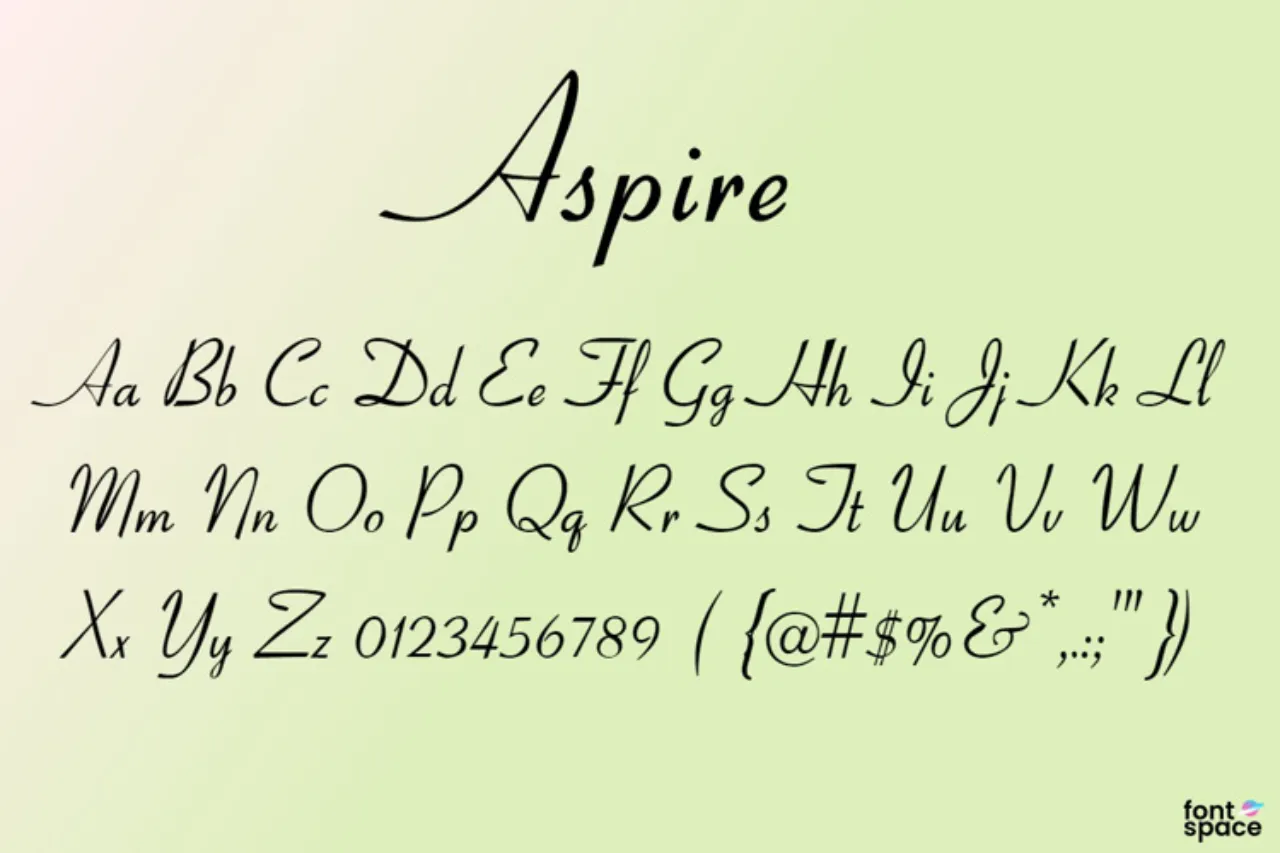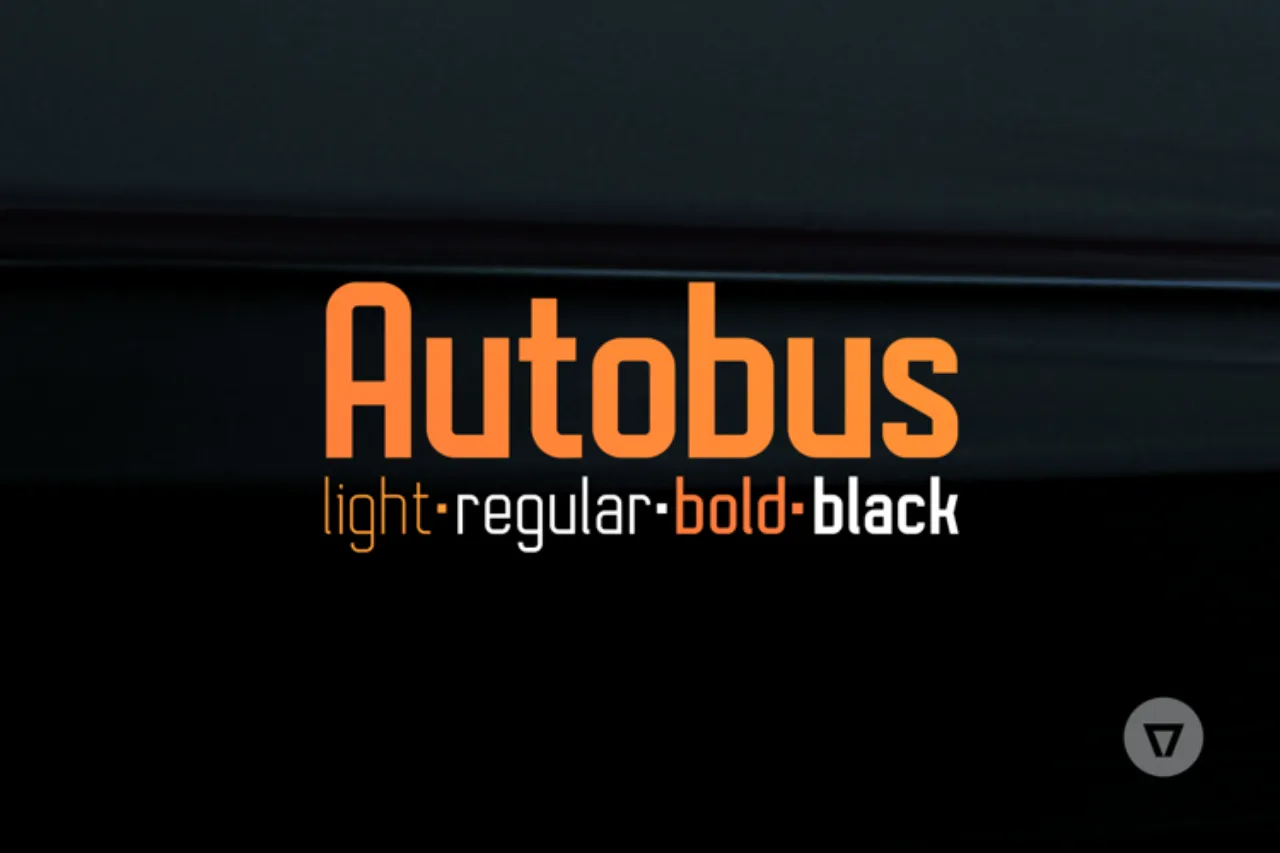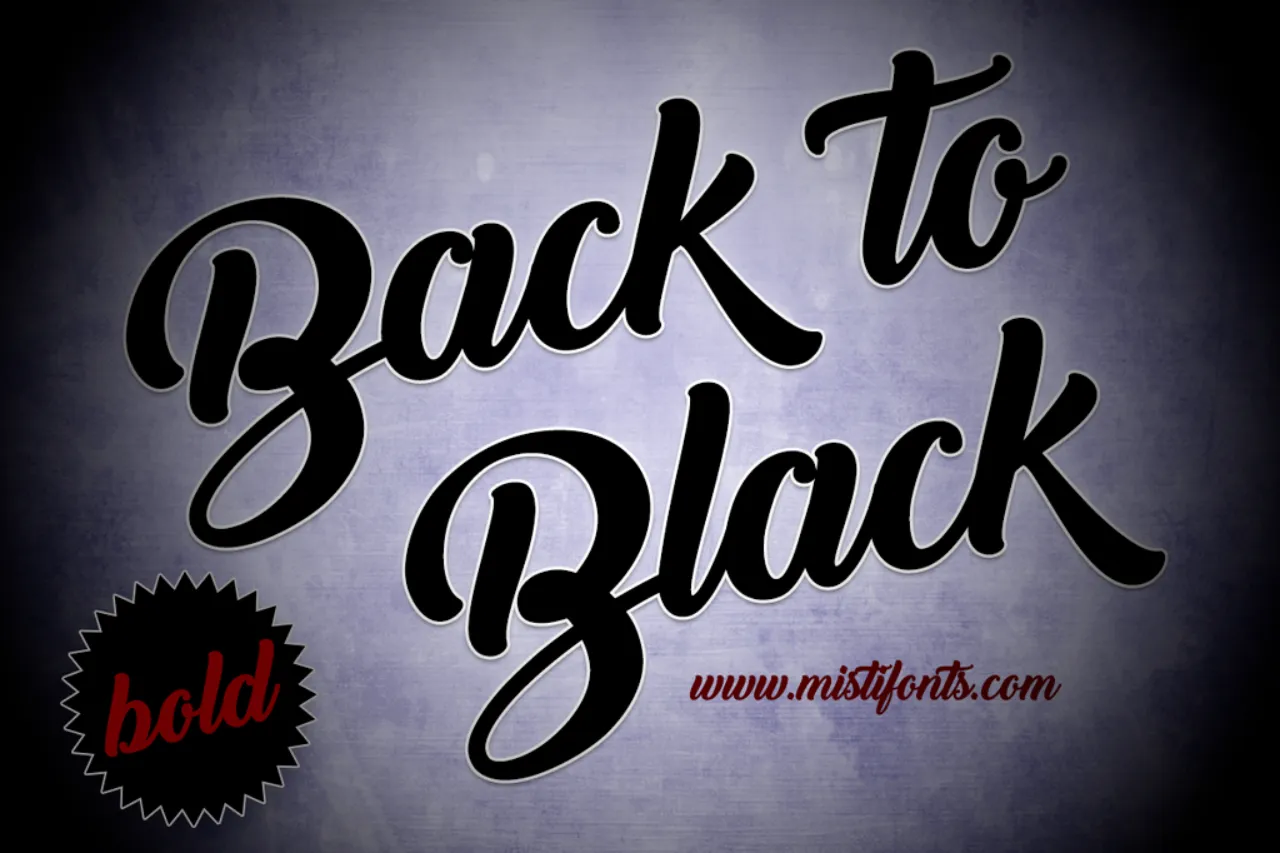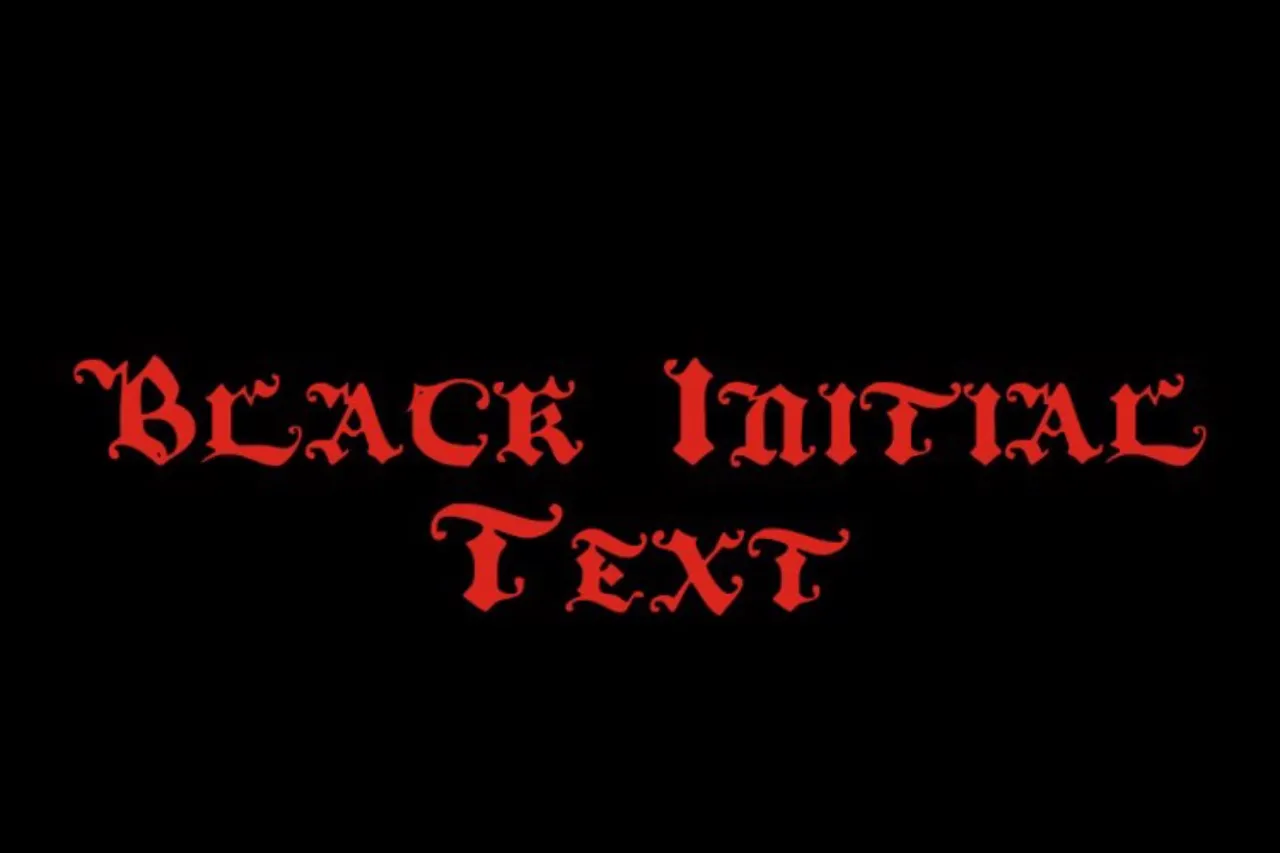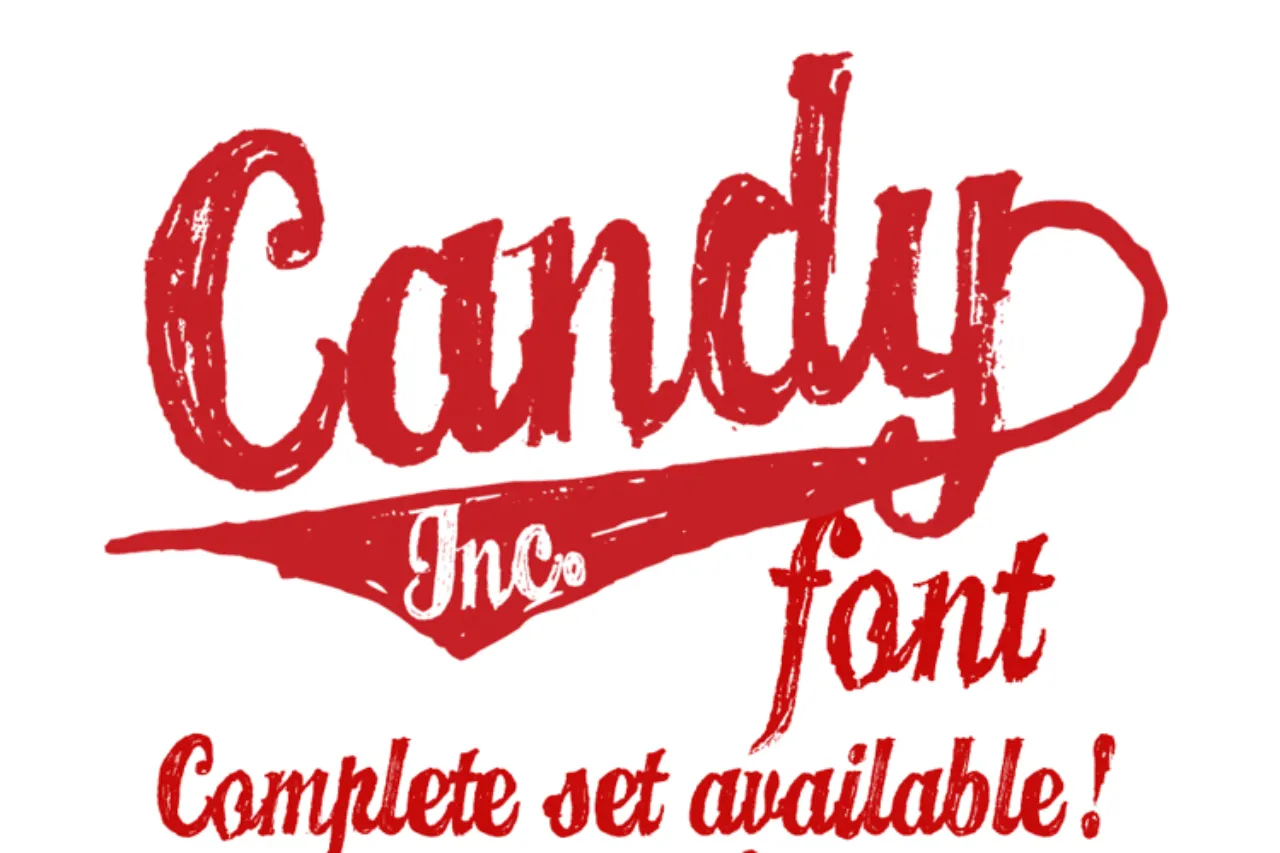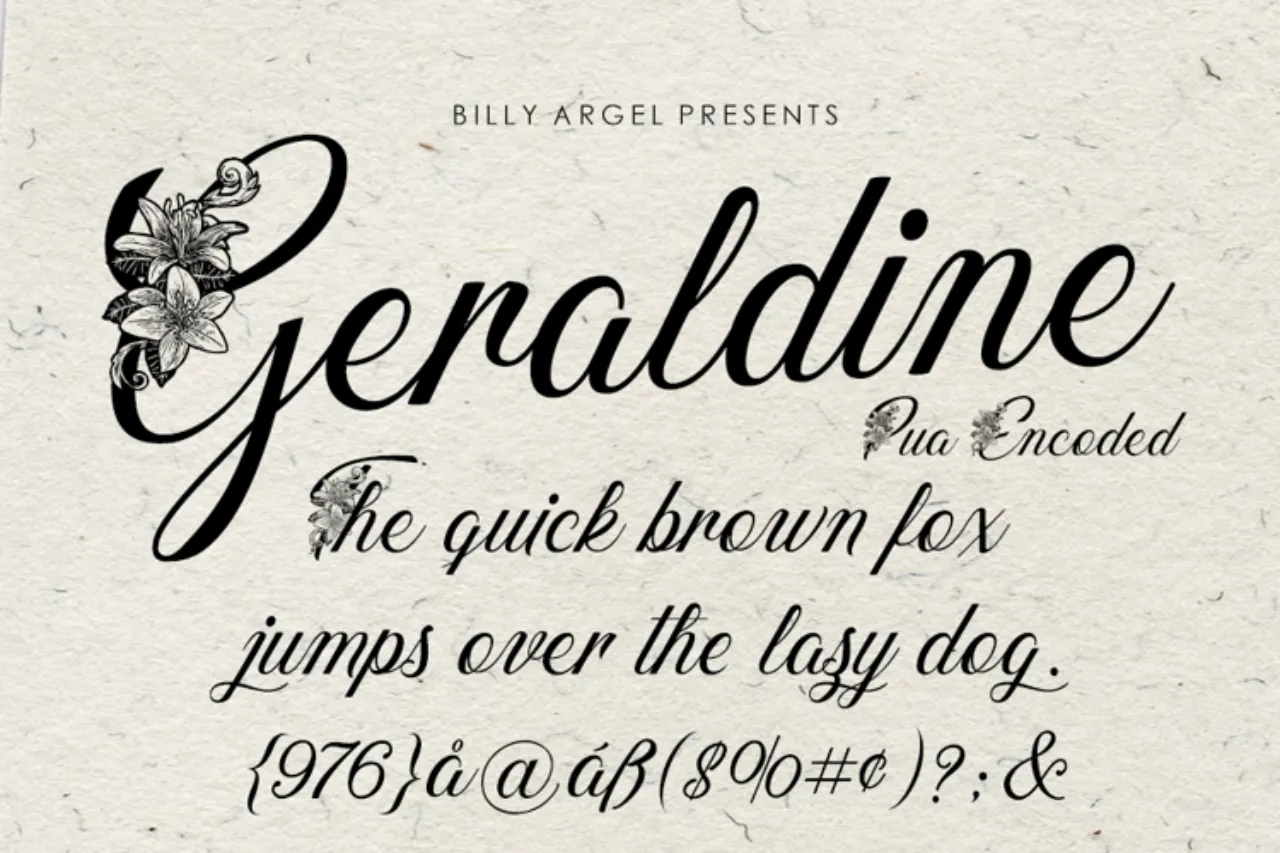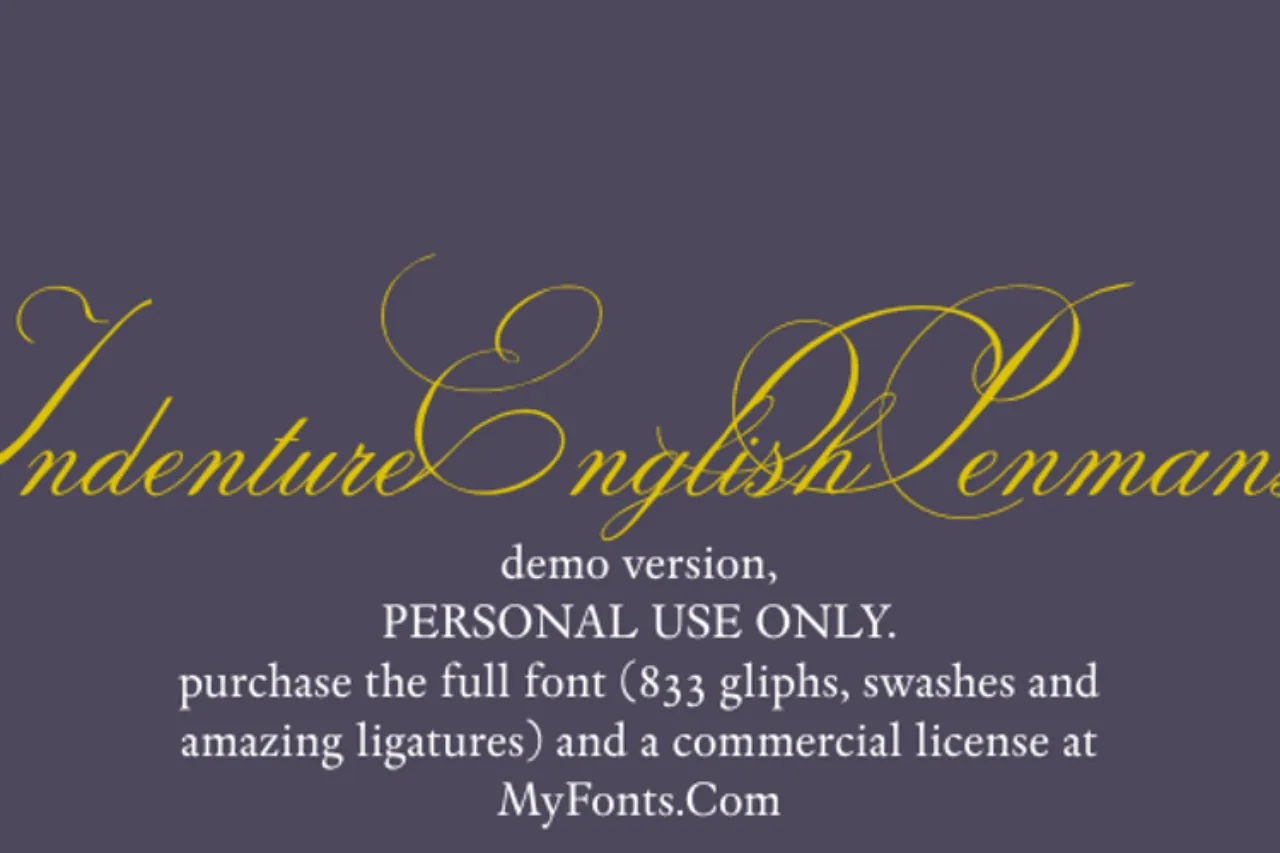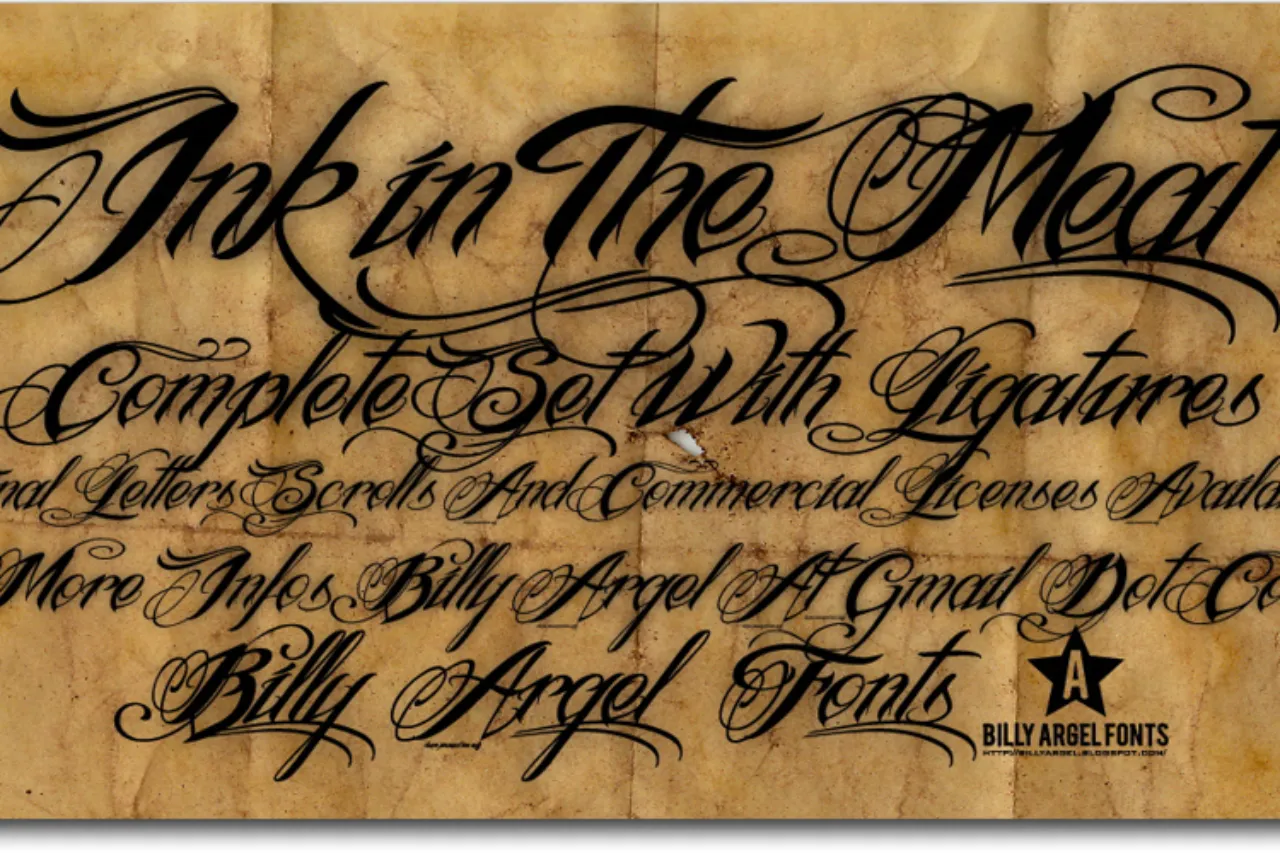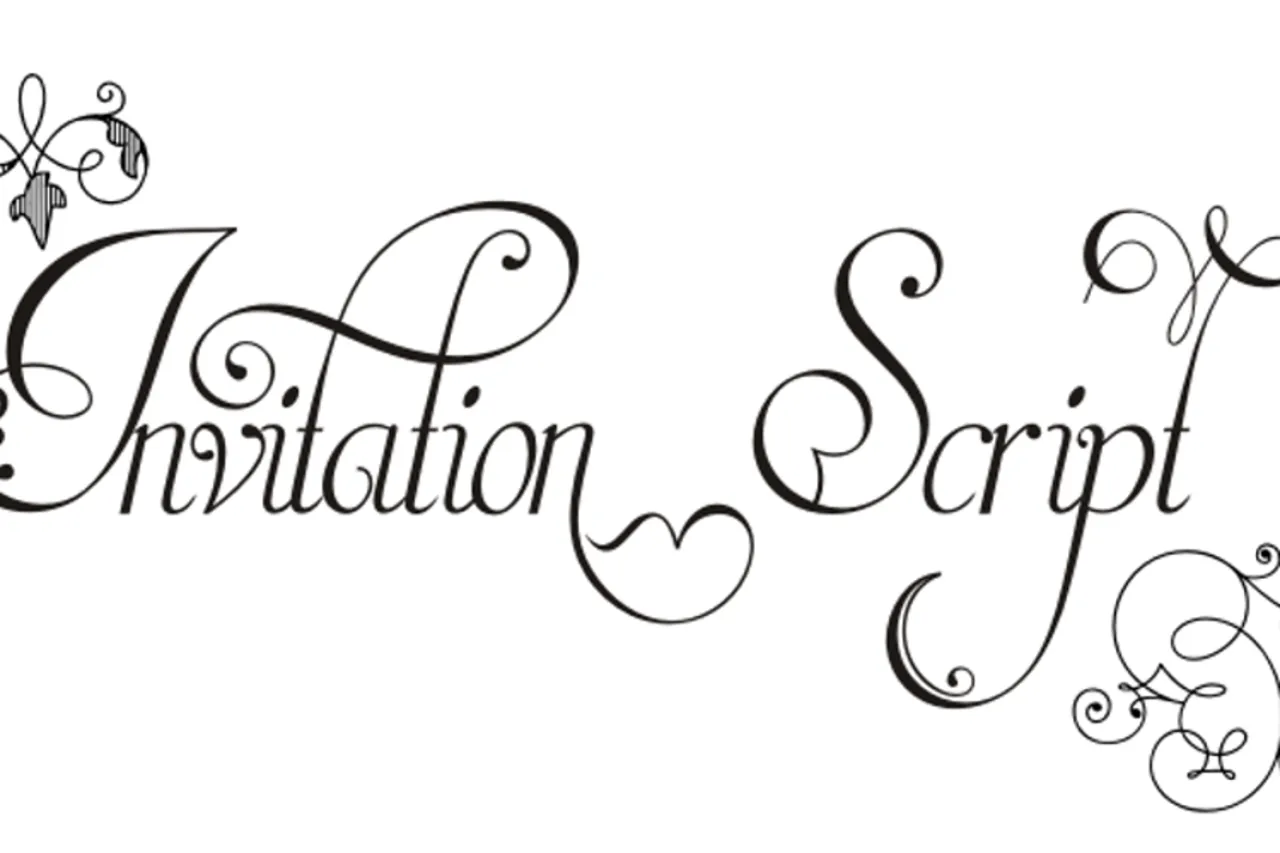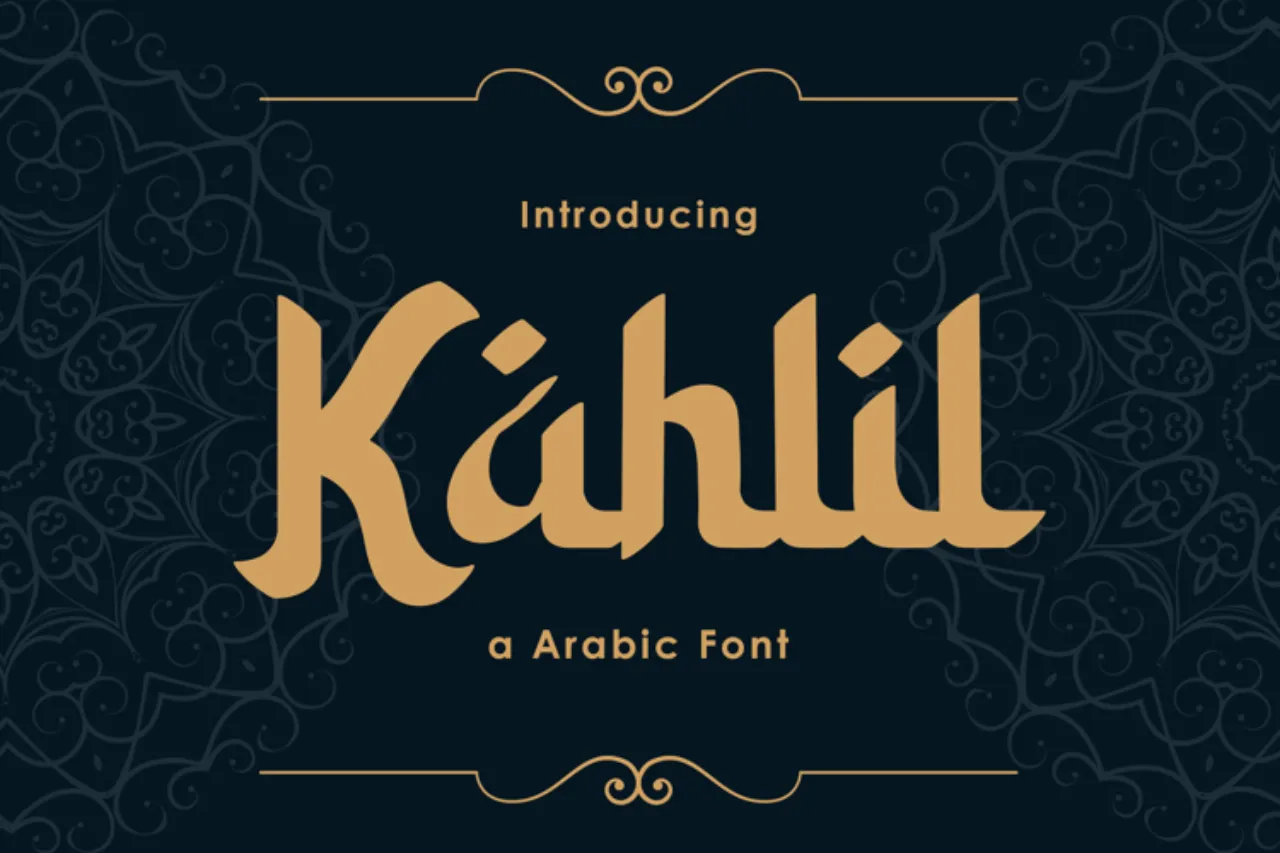
Font Sertifikat
25 Rekomendasi Font Sertifikat dan Link Downloadnya
Sertifikat dan piagam adalah salah satu dokumen yang cukup penting. Karena sertifikat dan piagam ini sering dipakai sebagai hadiah dari pencapaian seseorang setelah mengerjakan sesuatu.
Oleh sebab itu, sertifikat harus didesain sebaik mungkin untuk meningkatkan kesan menarik. Salah satu yang harus diperhatikan desain sertifikat ialah pemilihan font-nya.
Nah lewat artikel ini, kami akan memberikan daftar font sertifikat dan piagam yang bisa kamu pilih. Kalau penasaran, langsung perhatikan pembahasannya di sini.
Daftar Font Sertifikat dan Piagam Unik dan Resmi
Secara garis besar, font sertifikat dan piagam sering memakai jenis handwriting. Namun terkadang sering juga memakai jenis font lain, tergantung event yang dicapai.
Untuk lebih jelasnya, langsung saja pilih salah satu dari rekomendasi daftar font sertifikat dan piagam seperti berikut:
1. Candy Inc Font
Font Sertifikat Candy Inc
Pertama kamu bisa pakai Candy Inc Font. Font buatan Billy Argel ini memiliki desain yang menarik dan gratis untuk dipakai. Baik untuk kebutuhan desain personal ataupun komersil.
Secara spesifik, desain Candy Inc Font ini mengusung kaligrafi. Namun di dekorasi sedemikian rupa sehingga memiliki kesan sedikit retro.
2. Adine Kirnberg Font Family
Font Sertifikat Adine Kirnberg Font Family
Ada juga Adine Kirnberg Font Family. Dari desain, font ini lebih terlihat modern dari yang sebelumnya.
Namun desain yang ada di font ini lebih simpel, tapi terlihat elegan. Sehingga cocok dipilih untuk membuat sertifikat acara formal.
3. Aspire Font
Font Sertifikat Aspire
Kalau kamu ingin desain font yang lebih sederhana lagi, kamu bisa pilih Aspire Font. Font ini juga sama terlihat elegan, namun dengan dekorasi yang berbeda.
Selain itu, font ini juga sangat cocok untuk dipakai dalam membuat sertifikat formal. Misalnya sertifikat workshop, kursus dan sebagainya.
4. Alex Brush
Font Sertifikat Alex Brush
Kemudian kamu juga bisa pakai Alex Brush. Font ini mengusung desain kaligrafi namun terlihat feminim.
Sehingga sangat cocok dipilih untuk pembuatan sertifikat, piagam, kartu undangan dan lainnya.
5. Ink In The Meat Font
Font Sertifikat Ink In The Meat
Ink In The Meal Font bisa jadi salah satu pilihan lain. Desain di font ini mirip seperti tato yang dipadukan dengan dekorasi lainnya, seperti kaligrafi.
Oleh karena itu, font ini sangat cocok untuk kamu yang ingin membuat sertifikat workshop di bidang tertentu. Utamanya sertifikat workshop pembuatan tato, seni rupa dan lainnya.
6. Chopin Script Font
Font Sertifikat Chopin Script
Selanjutnya ada Chopin Script Font. Secara spesifik, Chopin Script Font ini termasuk ke dalam jenis handwriting dengan desain elegan.
Sehingga tidak hanya cocok untuk membuat sertifikat dan piagam saja. Melainkan bisa juga dipakai untuk pembuatan kartu undangan nikah, tato, naskah musik dan sebagainya.
7. Invitation Script Font
Font Sertifikat Invitation Script
Invitation Script Font sebenarnya lebih sering dipakai untuk keperluan desain kartu undangan. Namun tidak jarang font ini juga dipakai untuk pembuatan piagam dan sertifikat.
Alasannya karena font ini sangat fleksibel dari desainnya. Dimana font ini mengusung desain kaligrafi, namun terkesan formal sehingga cocok dipilih untuk membuat sertifikat.
8. Great Vibes
Font Sertifikat Great Vibes
Kalau kamu ingin font yang memiliki desain sedikit simpel, Great Vibes ini bisa jadi pilihan. Alasannya karena desain di font Great Vibes ini tidak terkesan terlalu berat seperti sebelumnya.
Namun tidak juga terlalu sederhana, karena font ini memiliki desain melingkar di setiap karakter untuk mempercantik sertifikat yang akan dibuat.
9. Quigley Wiggly Font
Font Sertifikat Quigley Wiggly
Lalu untuk kamu yang sedang mencari font sertifikat kasual, Quigley Wiggly ini menurut kami sangat cocok.
Alasannya font ini masih sangat mudah untuk dibaca. Namun juga mengusung desain kaligrafi, dimana setiap karakter saling tersambung.
10. Indenture English Penman Font
Font Sertifikat Indenture English Penman
Misalnya kamu ingin memakai font format italic, Indenture English Perman ini bisa kamu pilih untuk sertifikat tersebut.
Tidak hanya mengusung format italic, font ini juga memakai desain kaligrafi supaya memiliki kesan lebih elegan. Font ini sangat cocok dipilih untuk membuat sertifikat, periklanan dan lainnya.
11. Allura Font
Font Sertifikat Allura
Allura Font adalah versi desain sederhana dari font sebelumnya. Di font ini juga mengusung format italic dan desain kaligrafi, namun lebih smooth.
Kahlil font ini sangat cocok untuk membuat sertifikat tertentu. Misalnya sertifikat pengadaan workshop agamis, pencapaian karyawan di perusahaan Islamic dan sebagainya.